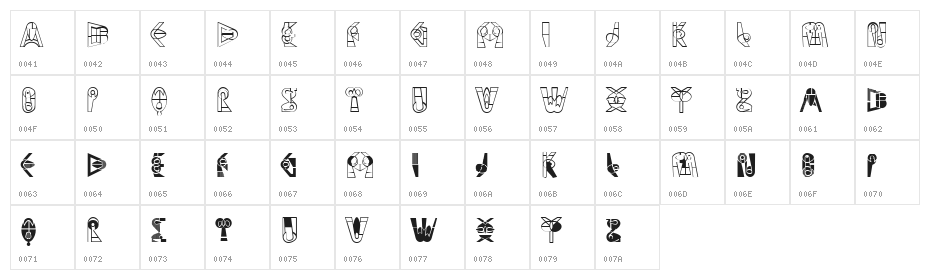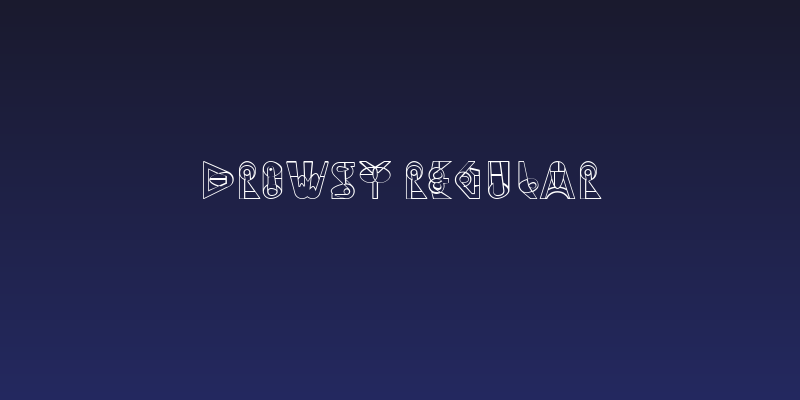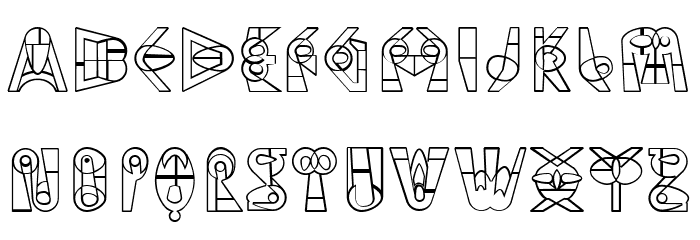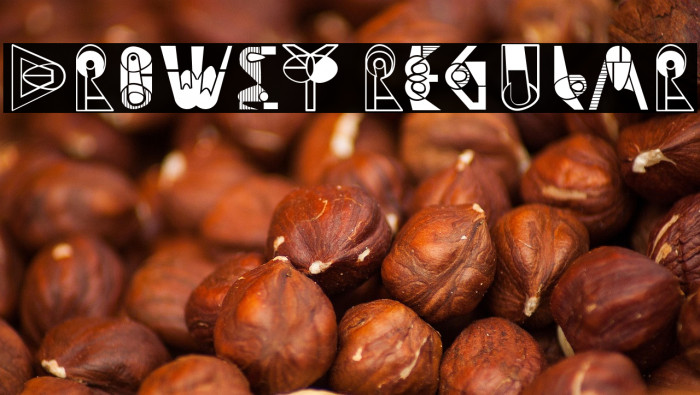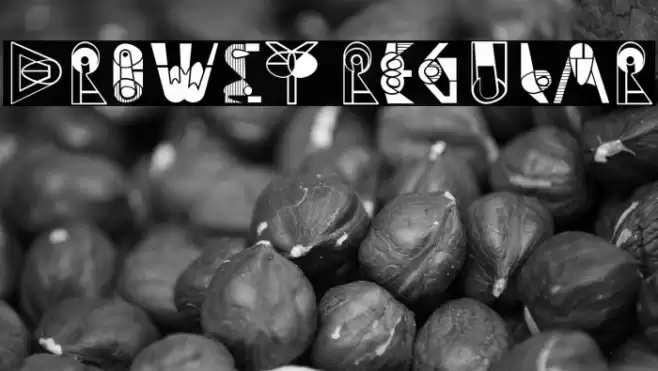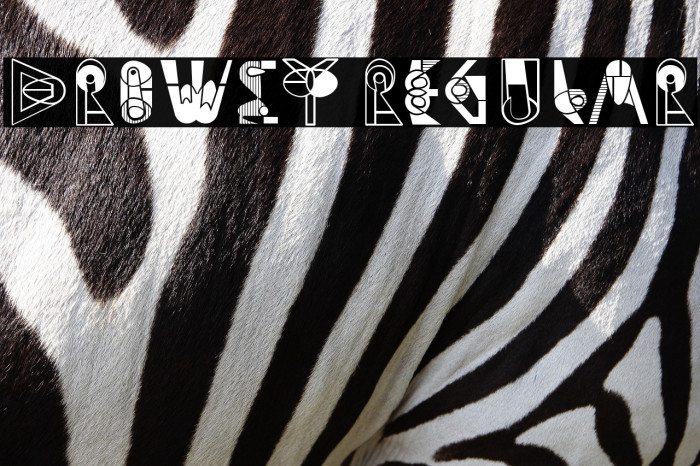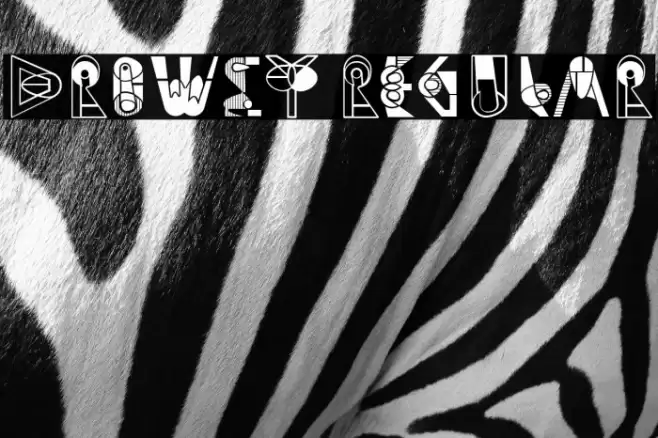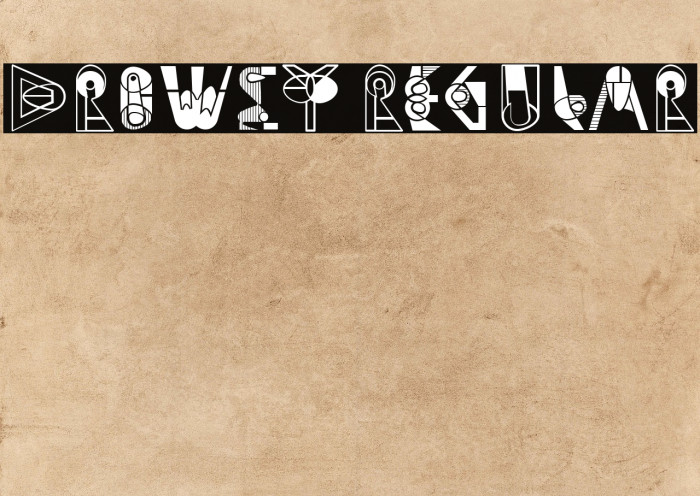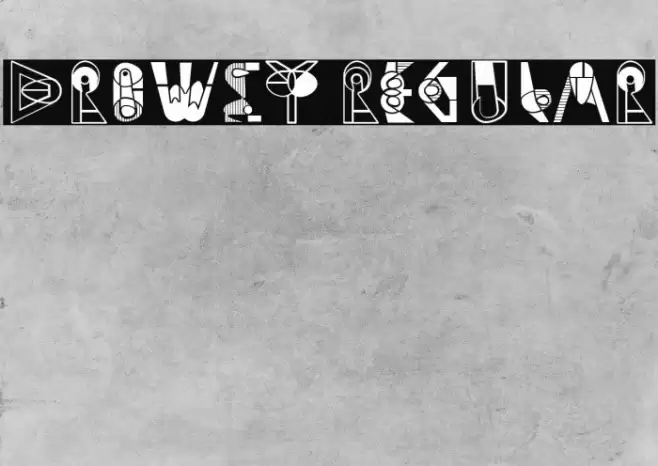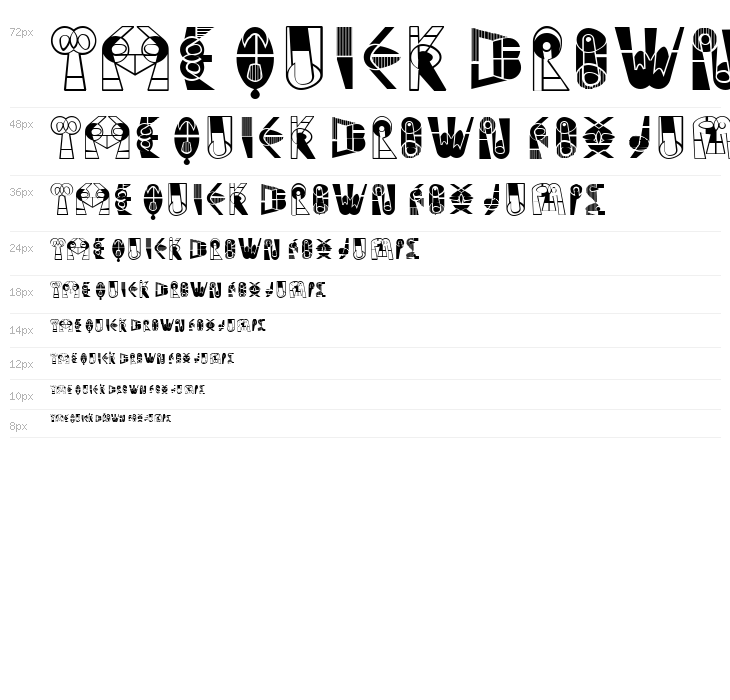
Drowsy Regular Font
| Gesamtstil | Modern, Avant-garde |
| Anwendungsfall | Headlines, Logos, Artistic projects |
| Vorgeschlagene Projekte | Ideal for use in artistic posters, album covers, branding for creative industries, and any project requiring a unique visual identity. |